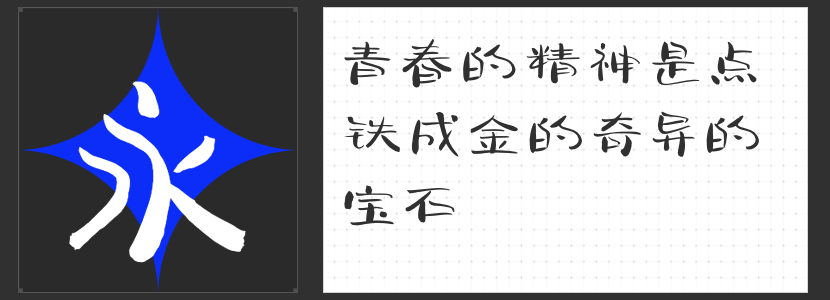
海报设计字体精选:四款匠心字库,赋予视觉独特灵魂
在海报设计的创意疆域中,字体不仅是信息的载体,更是视觉语言的核心表达。合适的字体能够瞬间抓住观者目光,传递设计理念,甚至成为作品记忆点。今天,我们精选四款风格迥异的非免费字库字体——励字开拓者简 特级黑、造字侠伏魔简繁 传神、造字侠醉春风简繁 苍劲、高手兵克清闲体,助你打造海报设计的视觉焦点。
一、励字开拓者简 特级黑
以硬朗线条勾勒秩序之美,励字开拓者简 特级黑以方正字形与适中重心奠定稳定基调。全直线笔画横平竖直,棱角分明,内部空间通过几何切割实现完美平衡。去钩化处理与竖直化撇捺设计,赋予文字镜像般的视觉张力,特别适合科技、工业、未来感主题海报。其网红流行用字库更满足年轻化传播需求,让设计自带话题属性。
二、造字侠伏魔简繁 传神
笔墨浓淡间见真章,造字侠伏魔简繁 传神以粗细对比强烈的笔触与夸张的勾提挑捺,演绎出传统书法的现代重构。中正结构中蕴含收放自如的韵律,每个字都如书法家挥毫落纸,充满动态生命力。适用于文化活动、影视海报或需要彰显文化底蕴的设计场景,让文字成为视觉叙事的主角。
三、造字侠醉春风简繁 苍劲
造字侠醉春风简繁 苍劲以自由率真的笔触打破方正桎梏,圆润点画与自然过渡的粗细变化,构建出灵动而不失稳重的字形风貌。其独特走势如春风拂柳,既保留手写温度,又兼具现代设计感。适合文艺展览、生活美学类海报,为画面注入呼吸感与人文温度。
四、高手兵克清闲体
扁扁的字形与洒脱的笔触,让清闲体自带萌系基因。手写体的不完美肌理与松弛结构,赋予文字亲切治愈的气质。无论是亲子活动、文创周边还是轻快风格的品牌海报,它都能以慵懒可爱的姿态,成为拉近观者距离的视觉糖分。
四款字体,四种美学表达——从几何秩序到笔墨张力,从灵动诗意到可爱治愈,它们不仅是文字的容器,更是设计师的创意画笔。选择契合主题的字体,让海报设计在信息传递与艺术表达间,找到完美的平衡支点。